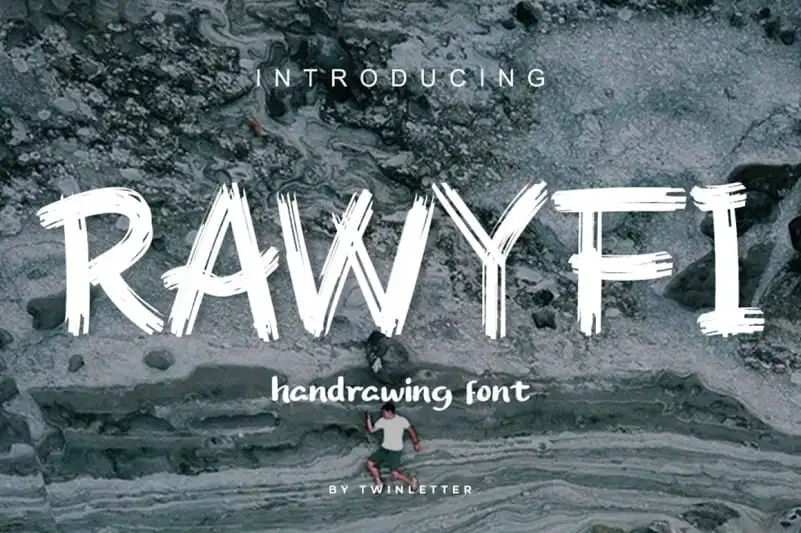
Rawyfi Brush Font
A Rawyfi Brush Font é uma fonte gráfica criada à mão com um estilo único, engraçado e versátil. Perfeita para usar em todos os seus projetos de design, seja para logotipos, assinaturas, rótulos, designs de embalagem, citações, títulos de capa, sinopse cinematográfica e muito mais. Não importa a situação, a Rawyfi fará sua mensagem destacar-se! Com certeza vai adicionar um toque único ao seu design. Seja você um designer ou uma pessoa que cria arte digital, vale a pena experimentar essa fonte, pois ela se encaixa perfeitamente em várias funções gráficas devido à sua originalidade e versatilidade.